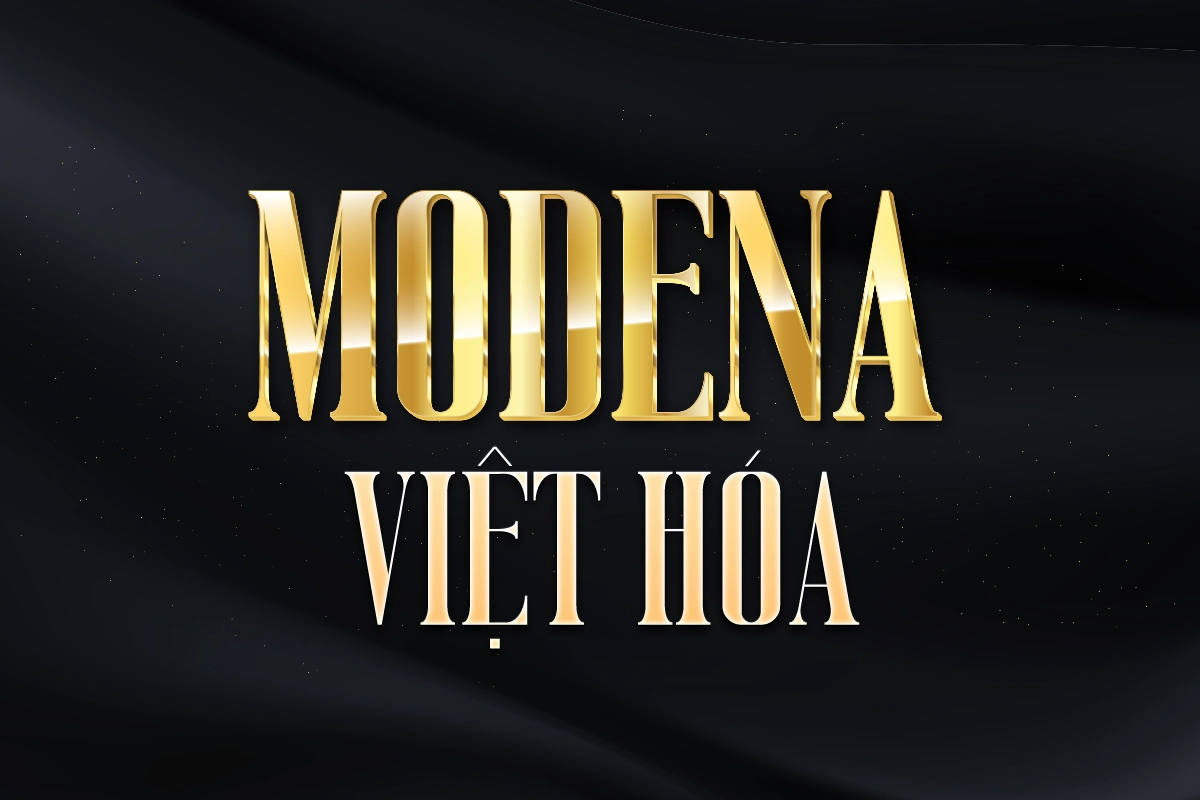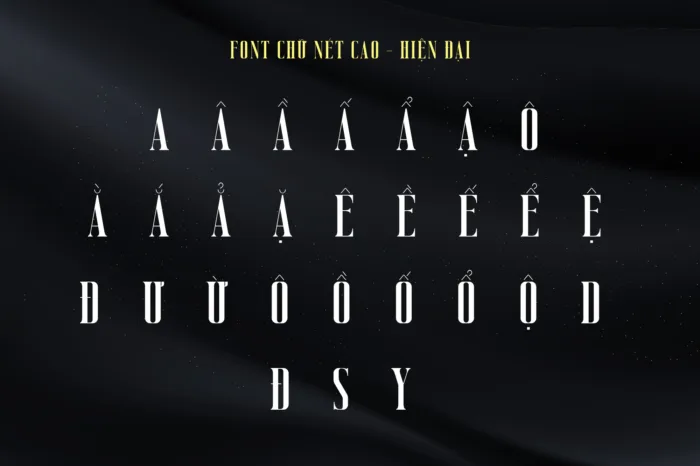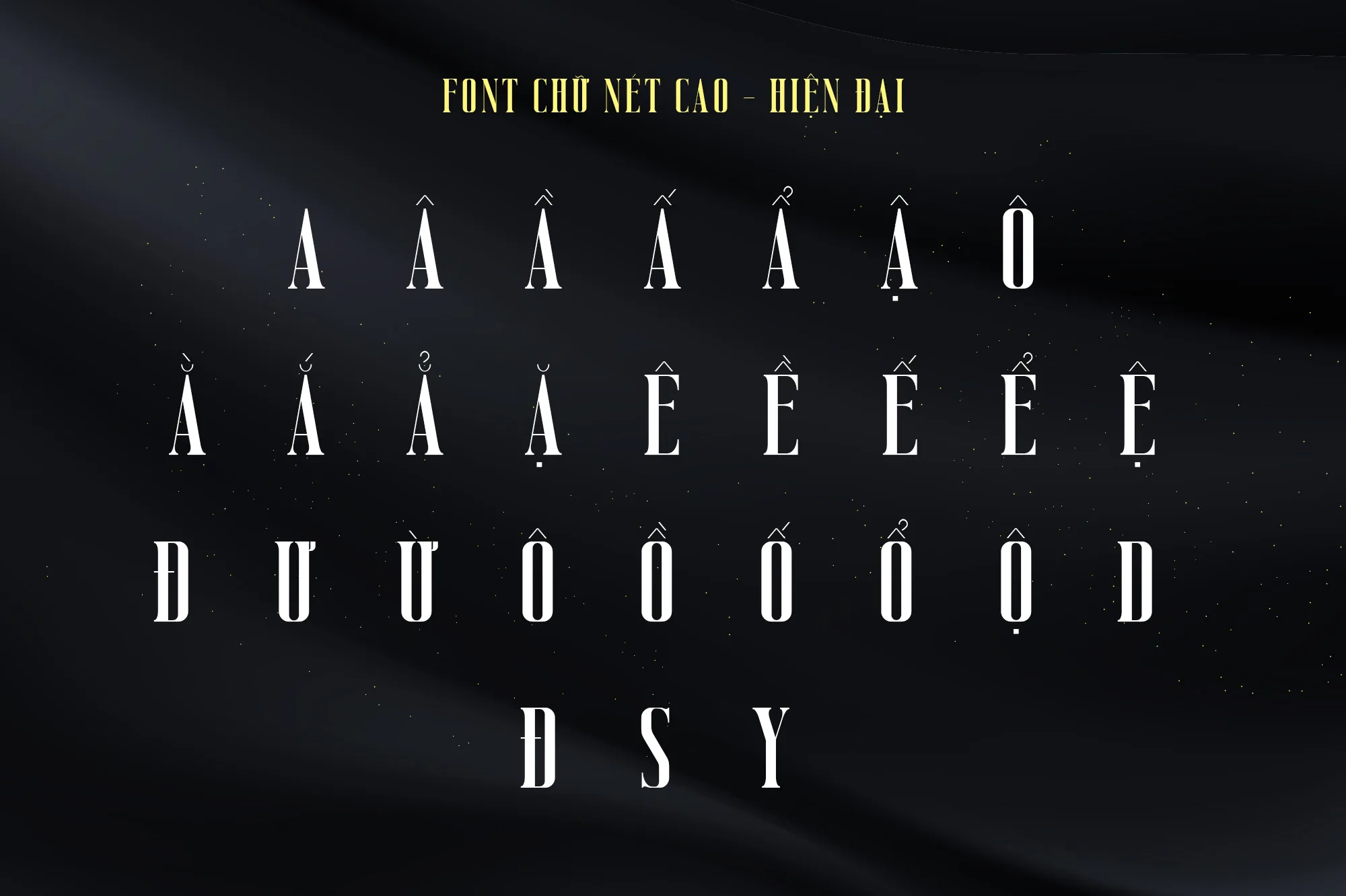
DVN Modena tiếng Việt – Font serif hẹp cao, thanh lịch và đầy khí chất
DVN Modena là bộ font serif mang dáng hình cao và hẹp, kết hợp giữa vẻ đẹp cổ điển và phong cách hiện đại. Với độ tương phản rõ rệt giữa các nét chữ và chiều cao nổi bật, font tạo nên cảm giác tinh tế, thanh mảnh nhưng đầy uy lực. Các ký tự được thiết kế chặt chẽ, tiết kiệm không gian ngang, giúp bố cục trở nên mạnh mẽ và có chiều sâu thị giác.
DVN Modena đặc biệt phù hợp cho các thiết kế bìa tạp chí, poster thời trang, thương hiệu cao cấp, hoặc tiêu đề trong các ấn phẩm biên tập. Phiên bản Việt hóa được tối ưu với đầy đủ dấu tiếng Việt, giữ nguyên tinh thần sang trọng và sắc nét của font gốc.